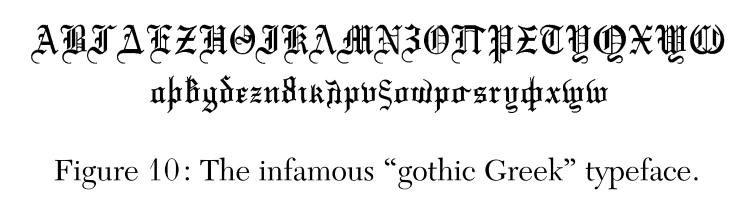
Zitate zu Gebrochenen Schriften
Das sehe ich auch so. Auf meiner Website habe ich das Werk so beschrieben:
»Im Frühjahr 1918, mitten in den Greul des 1. Weltkrieges, veröffentlichte
der Wolfenbütteler Bibliothekar Gustav Milchsack seine Schrift
»Was ist Fraktur? Eine wissenschaftliche Auseinander-
setzung mit dem Kommerzienrat Friedrich Sönnecken
in Bonn«, (Friedr. Vieweg & Sohn, Braunschweig 1918),
in der er die Bemühungen um eine Schriftreform scharf
kritisierte, aber auch schriftgeschichtliche Fehleinschätzungen
von Soennecken schonungslos aufdeckte. Die Lektüre dieses
Werkes vermittelt drastisch, mit welcher Unnachgiebigkeit
sich Befürworter und Gegner der Fraktur gegenüberstanden.
«
Auf meiner Seite Frakturverbot gibt es übrigens einen Link zum kompletten Werk.
Schwer vorstellbar, daß 1918 noch einer seinen Arm in irgend einem Kampf rühren wollte.
Während das alte Europa in den Schützengräben verblutet,
hofft Milchsack in nationalistischer Verblendung auch 1918
noch auf eine Klärung der Schriftfrage und das Primat der
Fraktur nach Beendigung des Krieges.
Umso wichtiger war die Veröffentlichung von Matthias Mieses im Jahr 1919*.
Ich darf noch einmal zitieren:
»Nationalismus hat in der Schriftgeschichte nichts zu schaffen. Dieselbe religiöse
Sezession, die der Fraktur eine Heimstätte bei Finnen und Esten, protestantischen
Litauern und Masuren, Dänen und Schweden bereitete, hat diese auch in Deutsch-
land konserviert. Das ›Deutschtum‹ der Fraktur führt noch heute so manchen
guten deutschen Mann irre. Es gibt noch in der Gegenwart manche Deutsche,
die eine Steigerung ihres Nationalselbstbewußtseins darin sehen, wenn sie die
Fraktur als den Ausdruck des ethnischen Wesens des Deutschtums proklamieren.«
*Mieses, Matthias: Die Gesetze der Schriftgeschichte. Konfession und Schrift im Leben der Völker. Wien und Leipzig, 1919
Milchsack konnt noch nicht so viele Antikriegsfilme sehen und Antikriegsromane lesen wie wir und erlitt vielleicht auch privat keinen Verlust. Er war bei Ausbruch des Krieges über sechzig. Und das Nationalgefühl war zu dieser Zeit sehr mächtig. Also verstehen kann man diese Äußerungen durchaus. Die Einstellung von Matthias Mieses war damals und für die folgenden zwanzig Jahre eher die abweichende Position.
Das Untereinanderwerfen der Fraktur- und Antiqua-Schriften auf Titeln
u. dergl. ist, wo der Mangel an passenden Schriften es nicht durchaus erfordert,
streng zu verpönen.
Hermann Neubürger: Leitfaden für Schriftsetzer-Lehrlinge, Dessau, 1842
Das Untereinanderwerfen der Fraktur- und Antiqua-Schriften auf Titeln
u. dergl. ist, wo der Mangel an passenden Schriften es nicht durchaus erfordert,
streng zu verpönen.
Das kunterbunte Untereinanderwerfen jeglicher verschiedener Schriften auf Titeln
u. dergl. ist, wo der Mangel an passenden Schriften es nicht durchaus erfordert,
streng zu verpönen.
»Es mag wohl dem in den französischen Kriegen erwachten Nationalitätseifer
zuzuschreiben sein, dass in Deutschland die Versuche, die Fractur abzuschaffen,
zu Anfang dieses Jahrhunderts ganz aufgegeben wurden.«
Karl Faulmann
»Illustrierte Geschichte der Buchdruckerkunst«
Wien, Pest, Leipzig, 1882
»Die Schriften … aus der Hand des damals berühmten Schriftgiessers
Zingk in Wittenberg, … aus der Trattnerschen Giesserei in Wien, haben
so wenig Anspruch auf Schönheit, dass man es sehr begreiflich findet,
wie sich die Gunst der deutschen Leser von ihnen abwenden musste.
Damals war die deutsche Leserwelt so mit französischen Schriften vertraut
und an die Antiqua gewöhnt, dass Göschen es wagen konnte, deutsche
Romane in Antiqua zu drucken. Es ist zu beklagen, dass dieses Beispiel
nicht mehr Nachahmung fand, dass die günstige Gelegenheit nicht benützt
wurde, um die Fracturschrift abzuschaffen, und die deutschen Buchdruckerei-
besitzer, welche noch heute den ihrem Betriebscapital unangenehmen
Dualismus der Schrift empfinden, dürfen es besonders beklagen. Die Fractur
hat keine grössere Berechtigung als die französische Batarde, sie ist ein
Schreiberproduct einer vergangenen Zeit und besitzt nicht den lapidaren
Charakter, welcher die Antiqua zu einer neuen Verjüngung befähigte.«
Karl Faulmann
»Illustierte Geschichte der Buchdruckerkunst«
Wien, Pest, Leipzig, 1882
Schön gesagt – auch wenn ich ein ausgesprochener Fan der französischen Bartaden* bin :nicken:
* Wie ist da die Mehrzahl? Eher französisch ›Batardes‹ oder eingedeutscht wie oben oder lieber einfach Bastardschriften?
Nicht wirklich ein Zitat, aber eine Antwort auf meine Frage:
Es gab/gibt ein gebrochenes polytonisches Griechisch?
Quelle: Yannis Haralambous, From Unicode to Typography , a Case Study : the Greek Script, 1999.
Deutsche Restaurants? Es gibt tatsächlich so etwas wie deutsche Küche? Zudem hat sich Deutschland, abgesehen von einer kurzen deutschen, präziser bayrischen, Herrschaft und der damit einhergehenden Bierkultur, dort nicht wirklich mit Ruhm bekleckert (Rehakles sei ausgenommen). Wenn ich schon Bier erwähne, vielleicht brauchte das irgendeine einheimische Brauerei für ihre Corporate Identity?
^Mir sieht diese schrift einfach zu zusammengebastelt aus. Solche einfach gespiegelten Elemente, wie im Sigma oder Omega gehen gar nicht.